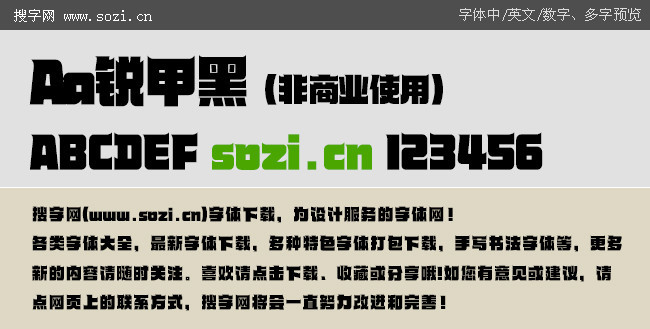
Aa銳甲黑
搜字網(wǎng)給大家提供一款Aa銳甲黑(非商業(yè)使用)中文字體下載,該字體是一款比較有力量的藝術字體,筆觸粗實,字形端正,給人一種非常粗壯有力的視覺感受,適用于平面宣傳設計、網(wǎng)頁設計、海報設計等應用(此字體為個人非商用版,商用可以聯(lián)系QQ:1006760504)。